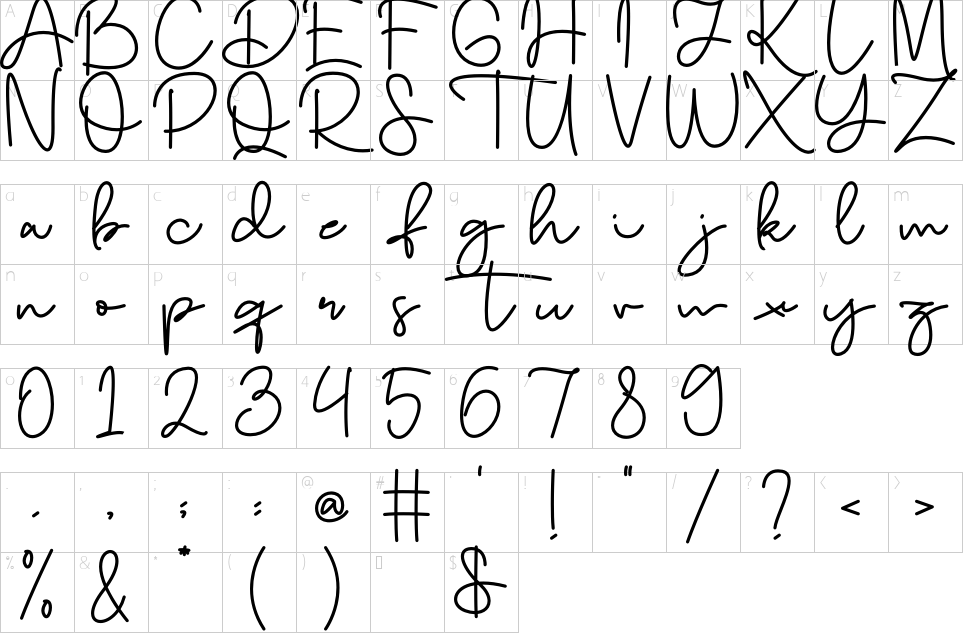
Dailymunt Font – Fonte Grátis
Dailymunt Font
A Dailymunt é uma elegante e versátil fonte que se destaca entre as muitas opções disponíveis no mercado. Desenhada por Jadatype, esta fonte garante um equilíbrio perfeito entre simetria e expressividade, tornando-a ideal para diversas aplicações em design gráfico. Seja ela utilizada para textos legíveis ou para dar vida a imagens visuais, a Dailymunt traz uma atmosfera moderna e contemporânea à sua produção. Com seu design cuidadosamente elaborado por Jadatype, esta fonte pode ser facilmente integrada em sites, aplicativos e projetos de design gráfico. E o fato de ela estar disponível para ambas as plataformas (Windows e Mac) torna-a ainda mais acessível e versátil para todos aqueles que buscam adicionar um toque único a suas criações digitais. Com apenas 9,585 downloads, pode-se dizer que a Dailymunt já conquistou seu lugar como uma fonte confiável e de alta qualidade no mundo dos designers gráficos.
Mapa de caracteres da fonte Dailymunt Font